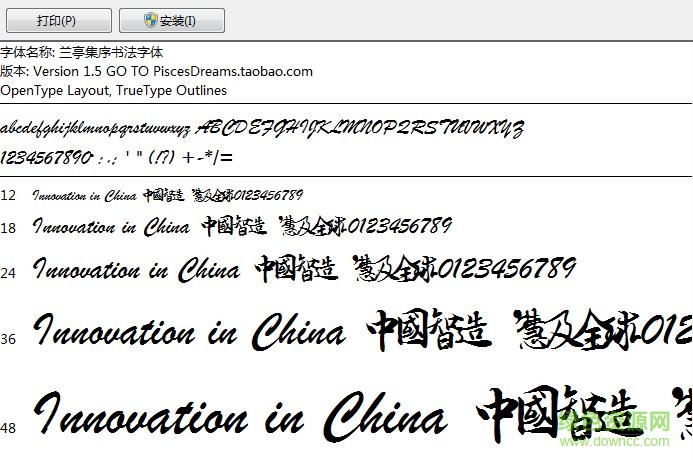
蘭亭集序書法字體是根據(jù)書圣王羲之的蘭亭集序中的書法打造的一款字體,延續(xù)王羲之用筆細(xì)膩,結(jié)構(gòu)多變的特色,有喜歡的朋友歡迎下載使用!
蘭亭集序書法字體是一款根據(jù)經(jīng)典蘭亭集序書法中的字體打造的電腦字體,這款字體完全延續(xù)蘭亭集序書法的特色,整體美觀大方,具有觀賞性!